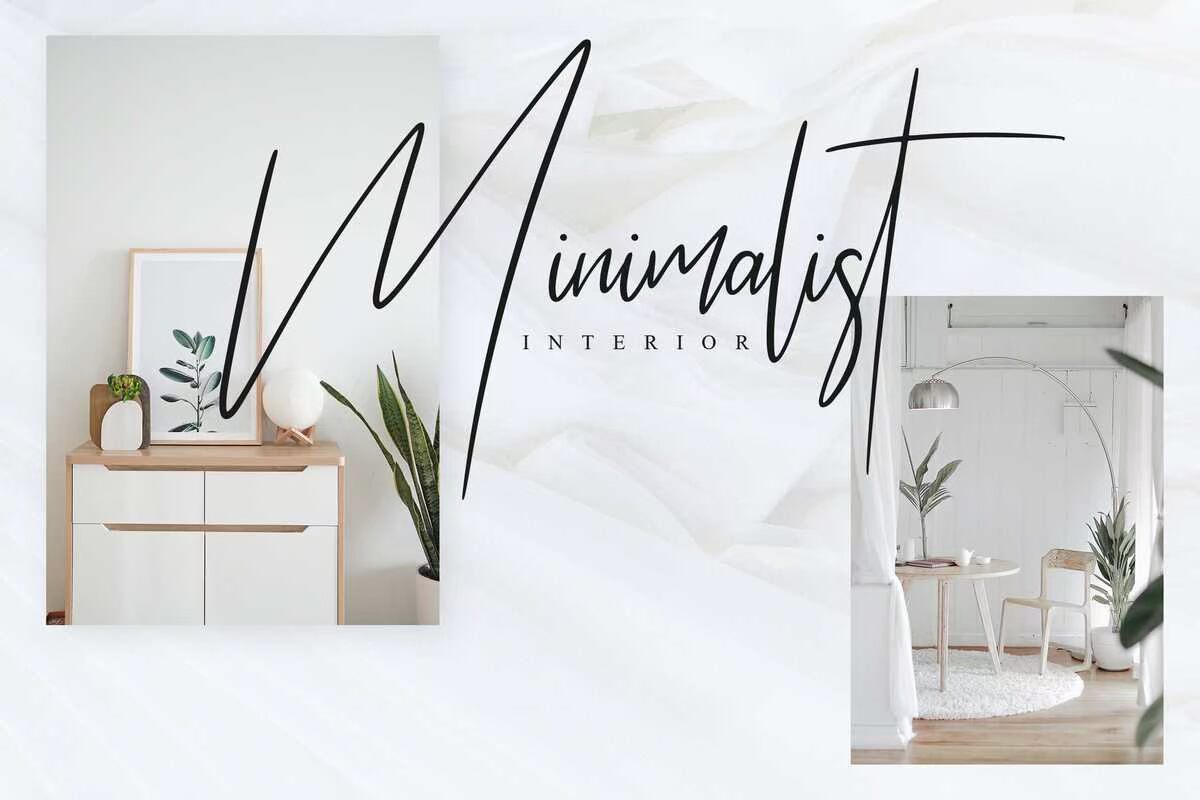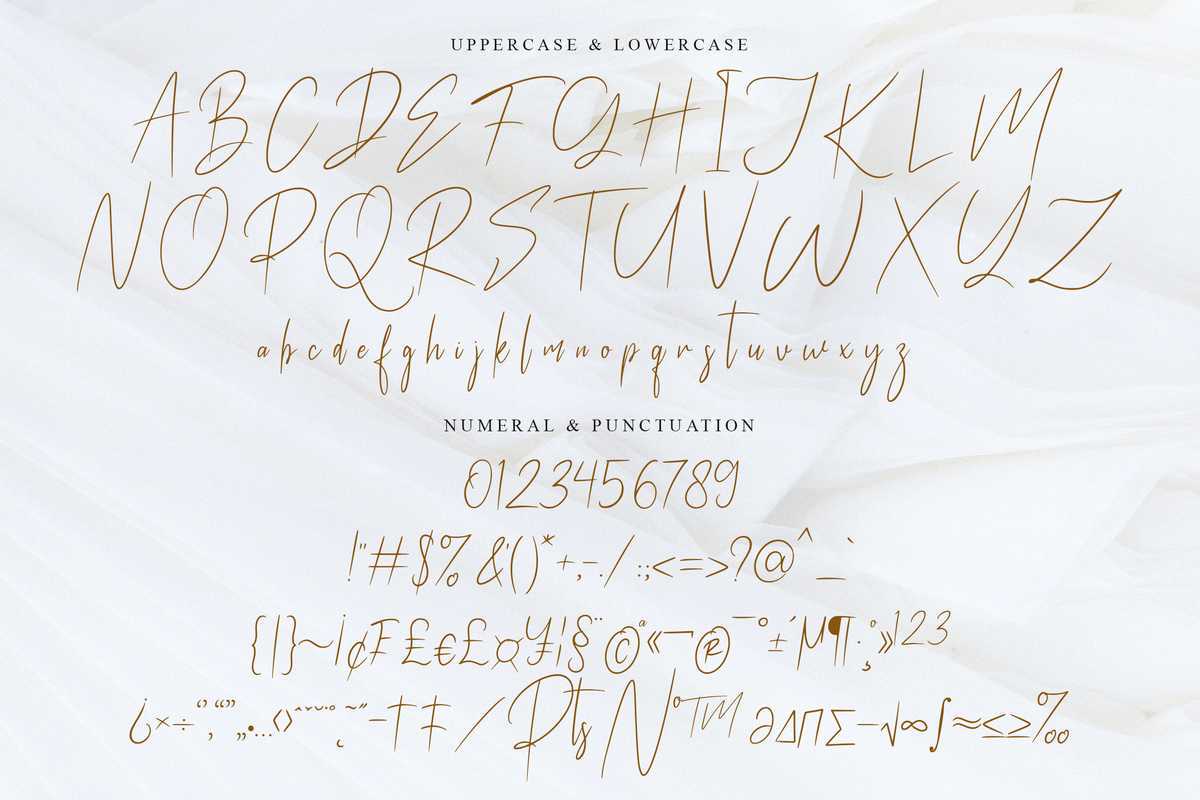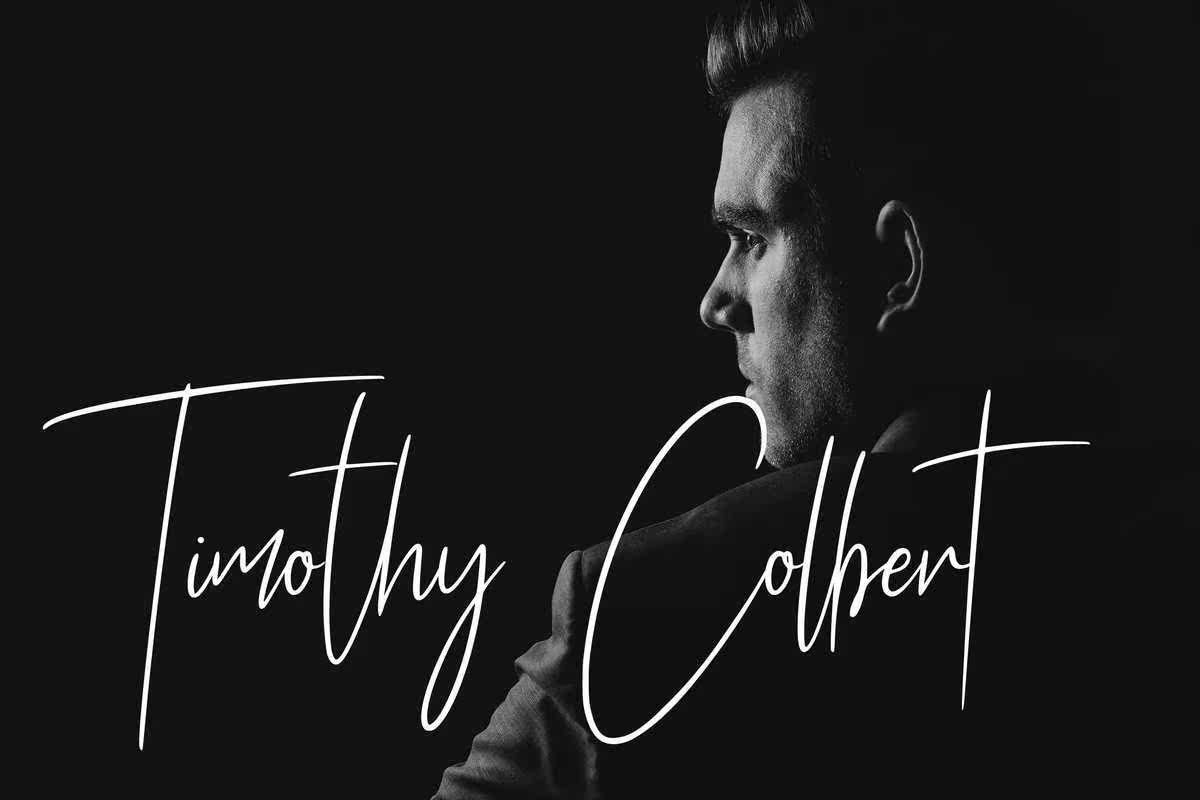
Mastherikurismoder和Timeless HandwritenFont。这款令人惊叹的字体是时尚的经典书法。它的特点是保留基线、平滑线、华丽的字形和令人惊叹的交替。Mastherikurismoder和Timeless HandwritenFont。这款令人惊叹的字体是时尚的经典书法。它的特点是保留基线、平滑线,华丽的雕文和令人惊愕的交替。